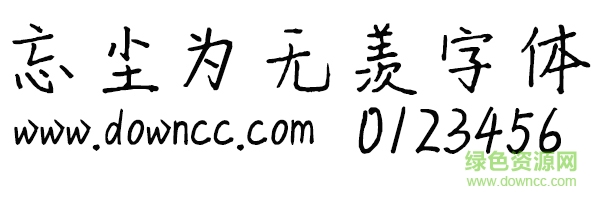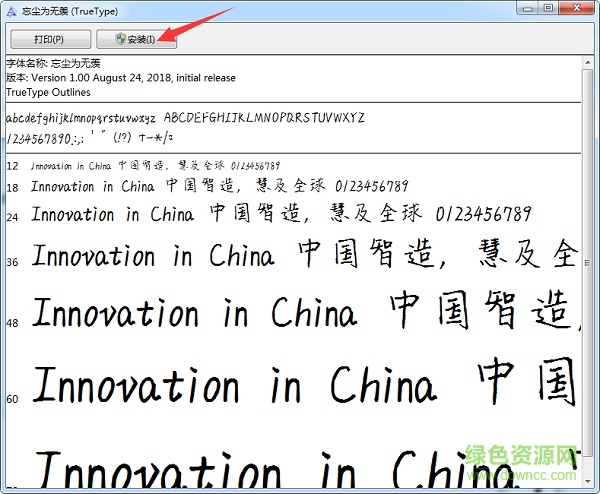
忘塵為無(wú)羨字體ttf是小編為大家提供了免費(fèi)藝術(shù)字體。這個(gè)字體既不中規(guī)中矩,也不潦草雜亂。書(shū)寫(xiě)字體和手寫(xiě)體差不多。所以在設(shè)計(jì)上使用的比較廣泛。歡迎網(wǎng)友們下載安裝。
字體家族:忘塵為無(wú)羨
字體風(fēng)格:Regular
字符數(shù):7165
字形數(shù):7150
字重:一般
字寬:中等(正常)
忘塵為無(wú)羨字體是由文道字庫(kù)設(shè)計(jì)師全新打造的,字體的意境就是紅塵焉有忘機(jī)語(yǔ),夢(mèng)醒愿為無(wú)羨人,藝術(shù)性跟實(shí)用性都兼有,字形框架非常的美觀,筆畫(huà)結(jié)構(gòu)看上去也非常的連貫流暢!可以廣泛的應(yīng)用在各個(gè)行業(yè)的字體設(shè)計(jì)方面!快來(lái)綠色資源網(wǎng)下載使用吧。